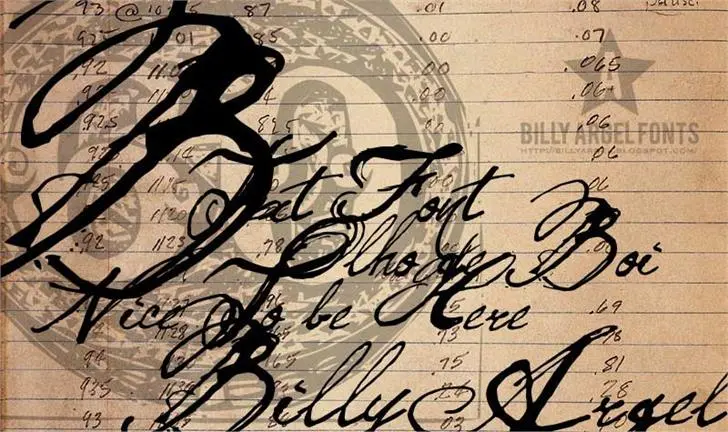
A ‘Olho de Boi’ é uma nova adição à ampla gama de scripts disponíveis para designers e criadores de conteúdo digitais. Lançada pelo designer Hamilton, esta fonte traz um estilo único e autêntico, perfeito para qualquer projeto que exige profunda personalização e arquitetura de texto. As linhas elegantes e a consistência na tipografia contribuem para criar uma experiência visual única e atrativa. Com foco no design comercial, é importante mencionar que a ‘Olho de Boi’ foi revisada recentemente para melhorar ainda mais seu uso em vários contextos. Para informações sobre direitos autorais ou assuntos relacionados ao uso comercial desta fonte, os interessados podem entrar em contato diretamente com o designer através do endereço  Além disso, a designer também mantém uma presença ativa no Facebook e tem um amplo portfólio de outras fontes disponíveis para consulta. Para explorar mais opções, é só acessar http://www.fontspace.com/billy-argel. Esta fonte traz um ar de modernidade e originalidade ao seu trabalho, permitindo que você atinja seus objetivos visuais de maneira inovadora e diferenciada. Engane-se se acredita não ter encontrado sua fonte favorita neste incrível catálogo de recursos gráficos.